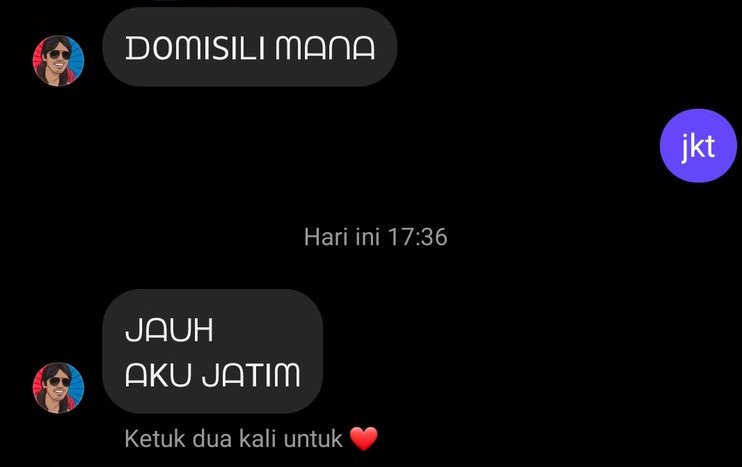
Teknologi.id - Belakangan ini, font "Dom Jatim" menjadi bahan perbincangan di berbagai platform media sosial seperti X (sebelumnya Twitter) dan TikTok. Font ini menarik perhatian karena tampilannya yang unik, dengan huruf kapital berbentuk membulat yang memberi kesan berbeda dari font pada umumnya.
Tren ini bermula dari sebuah tangkapan layar percakapan di Direct Message (DM) X. Dalam chat tersebut, seseorang menanyakan domisili dengan menggunakan font yang tidak biasa, berbunyi "domisili mana, jauh aku jatim." Tampilan teks yang mencolok ini kemudian memicu reaksi humor dari netizen, sehingga menyebar luas dalam bentuk meme dan tren baru di media sosial.
Kenapa Font "Dom Jatim" Bisa Viral?
Keunikan font ini terletak pada bentuk hurufnya yang berbeda dari font standar yang sering digunakan di ponsel. Karena tampilannya yang khas dan mudah dikenali, banyak orang mulai menggunakannya dalam berbagai konten kreatif, baik untuk humor maupun estetika.
Seperti halnya tren viral lainnya, font ini menjadi bentuk ekspresi kreatif di media sosial. Banyak pengguna yang memanfaatkannya untuk membuat meme dan teks lucu, yang semakin mendorong popularitasnya.
Cara Membuat Tulisan Mirip Font "Dom Jatim"
Saat ini, belum ada font resmi bernama "Dom Jatim," tetapi ada beberapa cara untuk mendapatkan tampilan tulisan serupa.
1. Menggunakan Font yang Mirip
Kamu bisa mencari font dengan gaya serupa di berbagai platform berikut:
- DaFont
- Google Fonts
- Canva Fonts (jika mendesain melalui Canva)
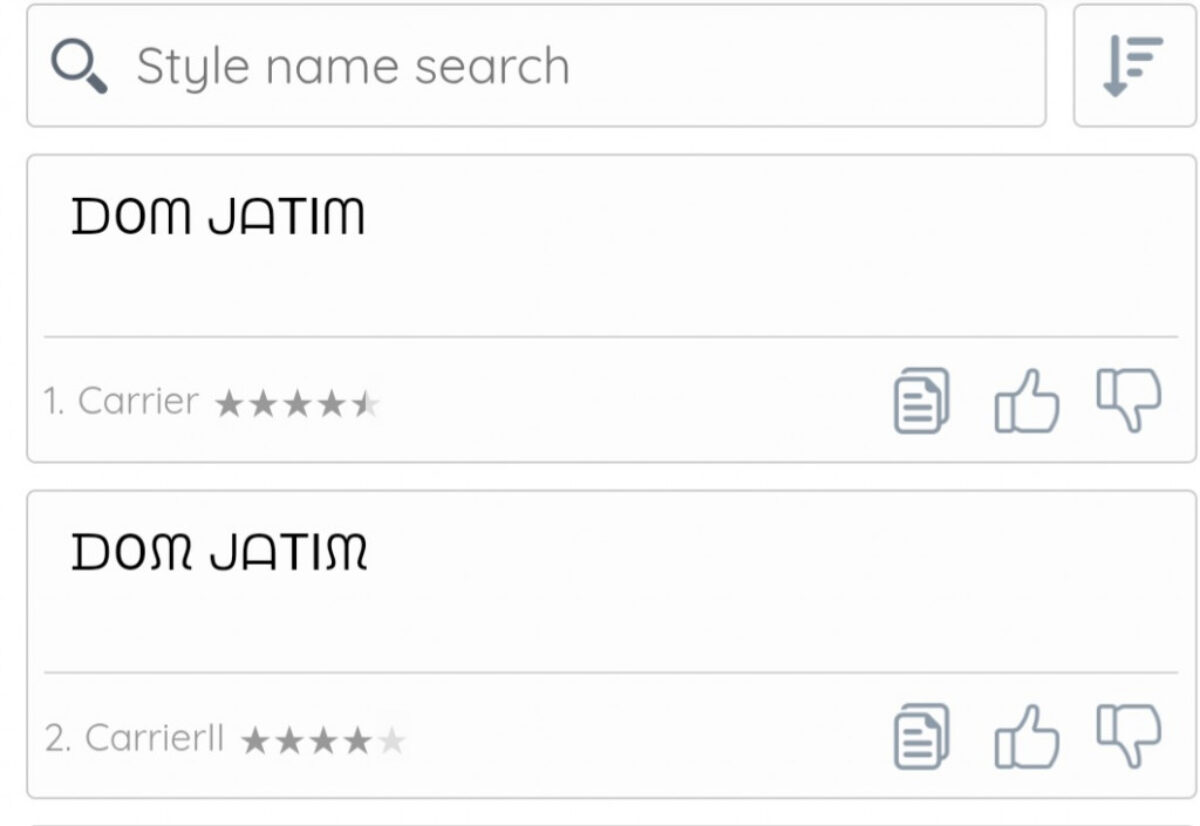
2. Menggunakan Font Generator Online
Jika ingin membuat teks dengan gaya "Dom Jatim" tanpa perlu menginstal aplikasi tambahan, kamu bisa memanfaatkan situs Messletters.
- Pilih font bernama "Carrier", yang memiliki tampilan mirip dengan font "Dom Jatim."